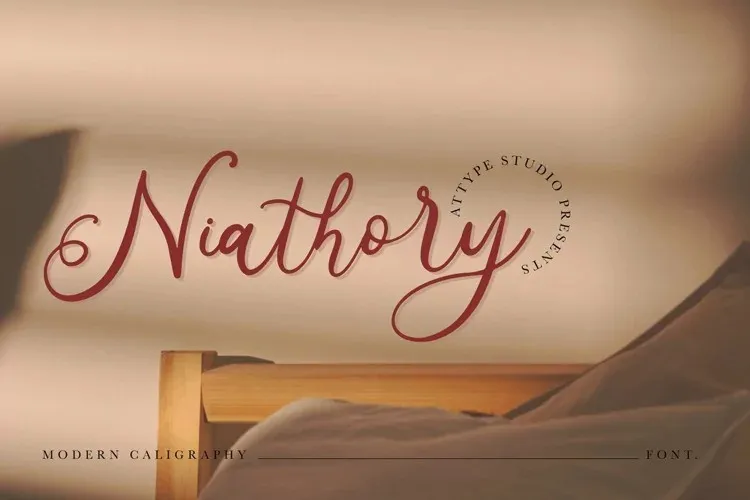
Niathory Font – Fonte Grátis
Niathory Font
A Niathory Font é uma delicateza moderna da Attype-Studio, criada especificamente para quem busca um traçado elegante e atual. Com seu estilo chamativo e sofisticado, essa letra de estilização é perfeita para criar fontes de texto incrivelmente legíveis e únicas para o uso em anúncios de casamento, cartões personalizados ou até mesmo como elementos adicionais em trabalhos gráficos digitais. Ela combina facilmente com outras tipografias para criar um layout arrojado e único. Seja você um designer buscando um elemento diferenciador que se destaque no seu próximo projeto de design, ou uma pessoa que simplesmente deseja adicionar um toque especial a seus cartões de aniversário ou mensagens pessoais, Niathory é a escolha perfeita. Com sua delicadeza e modernidade, essa fonte de estilo ajuda você a alcançar um resultado profissional incrivelmente único.